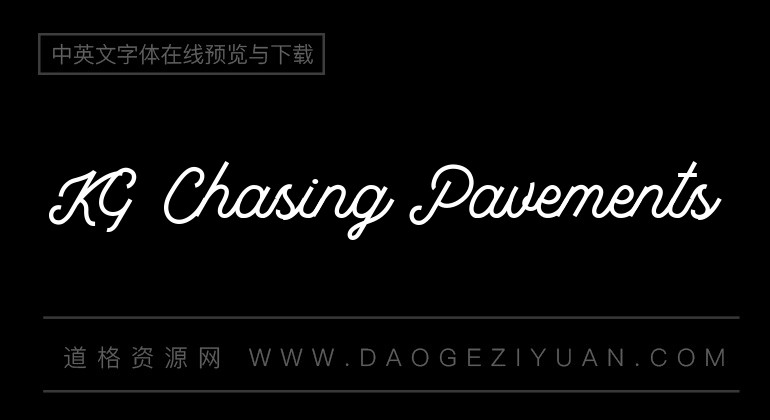
KG Chasing Pavements
KG Chasing Pavements 是一款细腻、柔和的草书字体,由 Kimberly Geswein 开发。这款字体具有优美的曲线,它以细节为重点,使用自然的线条和宽松的空间,以及自然的流动感,以及精致的笔画,让每个字母都充满美感。它可以用于创作各种类型的文字,从宣传海报到设计标志,都可以让您的文字充满活力和美感。
KG Chasing Pavements是一款非常不错的手写艺术字体,具有很好的视觉感,适合于文化类的宣传设计、商业类品牌的广告和产品包装设计以及个性化文字排版等较多场景。